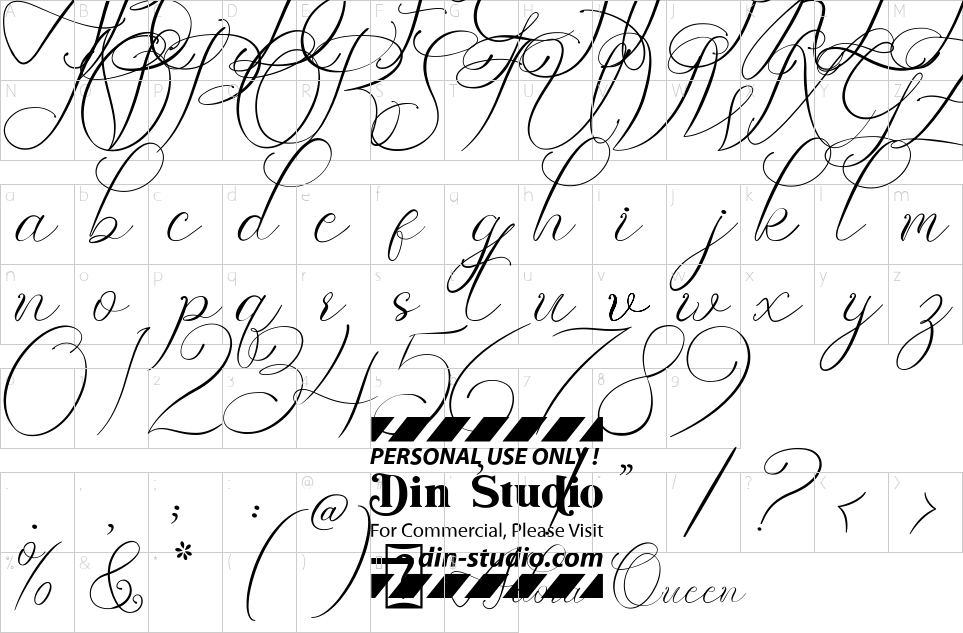
Adora Queen Font – Fonte Grátis
Adora Queen Font
A fonte Adora Queen é uma escolha perfeita para quem busca um estilo elegante e delicado, com uma elegância que se traduz em um charme sedutor. Desenvolvida por Donis Miftahudin, esta fonte oferece um charme única e sofisticado, adequada para diversos projetos visuais, como headlines, logotipos ou materiais de design gráfico de alto nível. Com apenas 377 downloads, a Adora Queen não apenas se destaca, mas também se torna um ícone no universo das fontes gratuitas. Seja você um designer de aplicativos ou um profissional do design gráfico, a Adora Queen é uma escolha inteligente que combina perfeitamente com seu estilo. Instale-a agora e transforme seu design em algo excepcional.